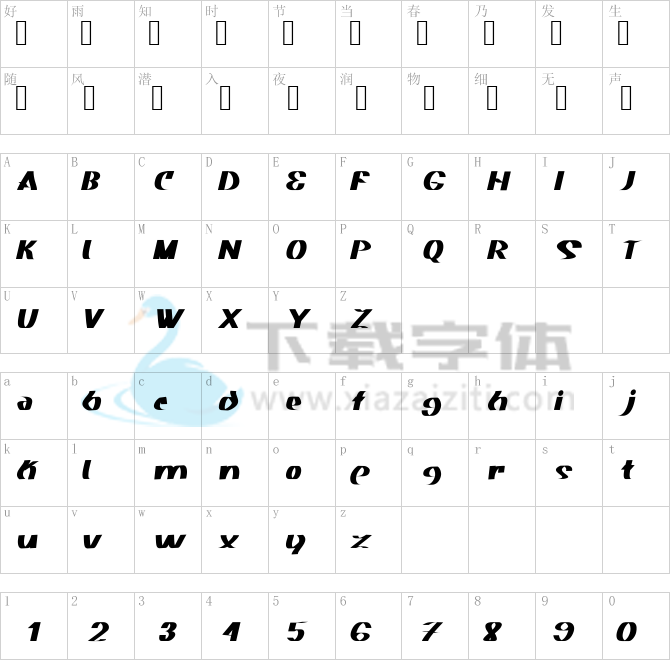
Akasic.ttf字体下载,这款字体结构工整、笔画清晰,兼顾美观与易读性,适用于标题、正文、海报、包装、LOGO 等多种场景。字形优雅稳定,风格百搭耐看,适配日常排版与创意设计,让文字呈现更舒适、更具质感。Akasic.ttf字体下载一笔一画,皆是细节,以均衡的比例、流畅的线条打造舒适视觉体验,字形端正大气,风格简约现代。无论是商业设计、品牌宣传还是日常排版,都能轻松驾驭,让文字更有格调与力量。Akasic.ttf字体下载字体下载。